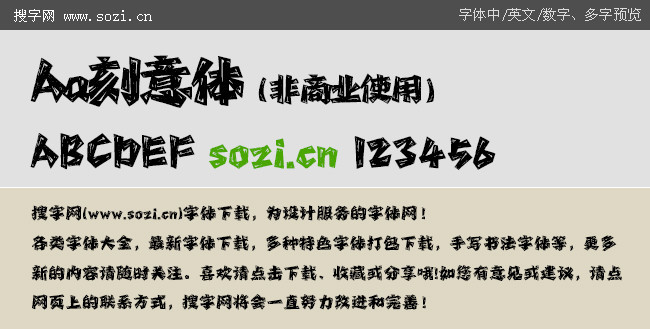
Aa刻意體
搜字網(wǎng)給大家提供一款A(yù)a刻意體(非商業(yè)使用)字體下載,這款字體是一款極具個(gè)性的藝術(shù)字體,風(fēng)格比一般的字體更有特色,連貫字跡顯得干練而不凌亂,清新簡(jiǎn)明,具有很好的視覺(jué)感。適合書(shū)裝設(shè)計(jì)、包裝設(shè)計(jì)、海報(bào)設(shè)計(jì)等應(yīng)用(此字體為個(gè)人非商用版,商用可以聯(lián)系QQ:1006760504)。